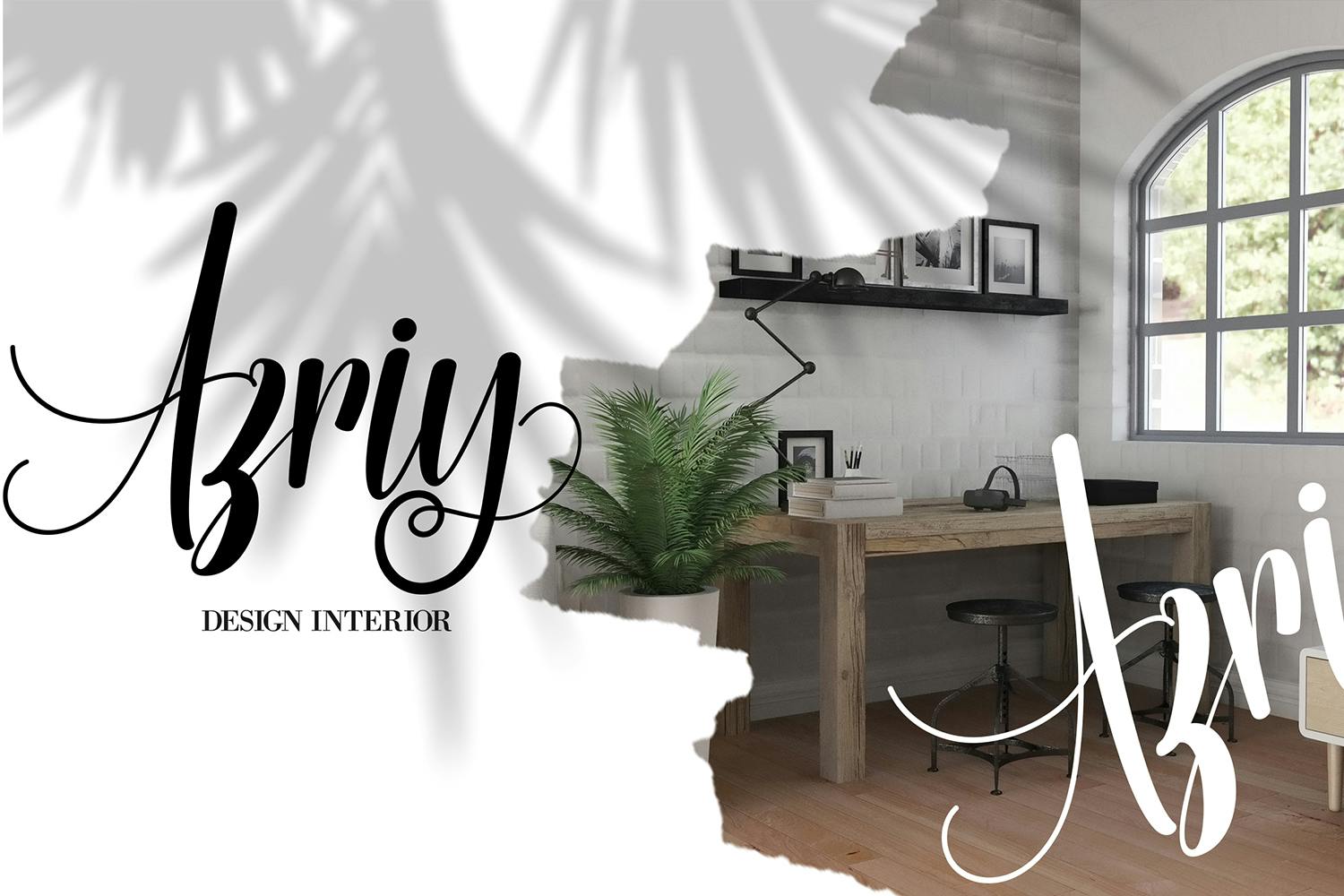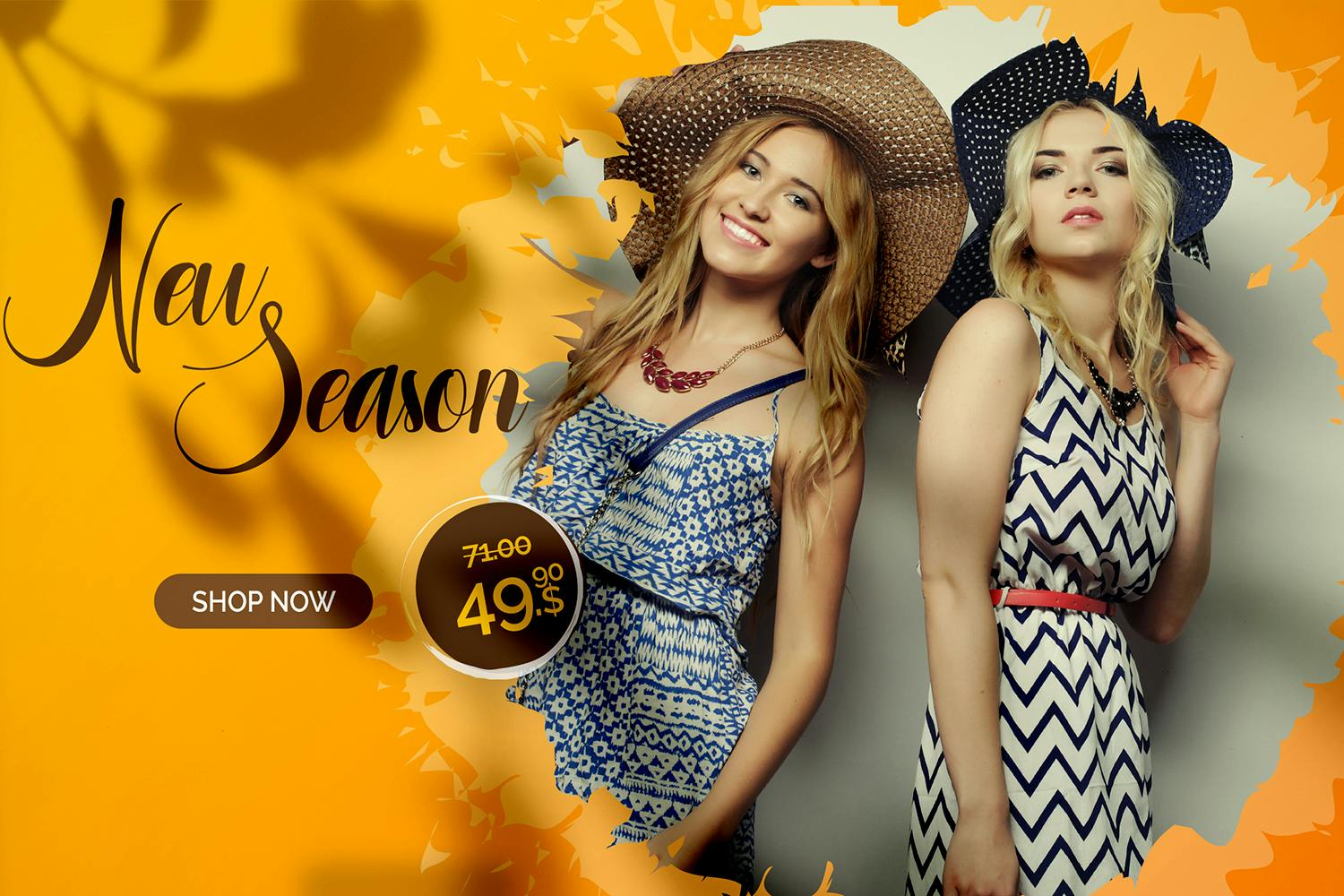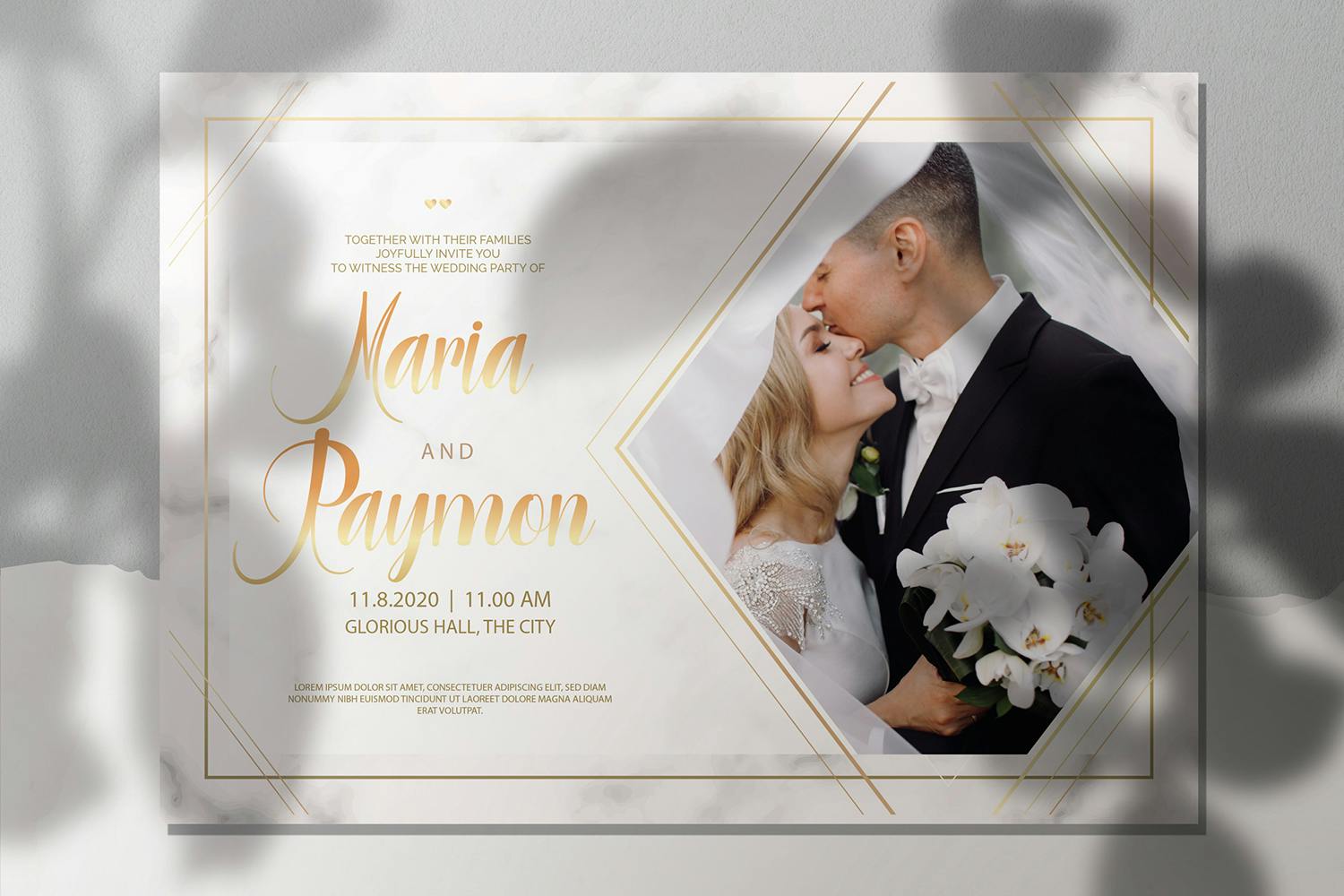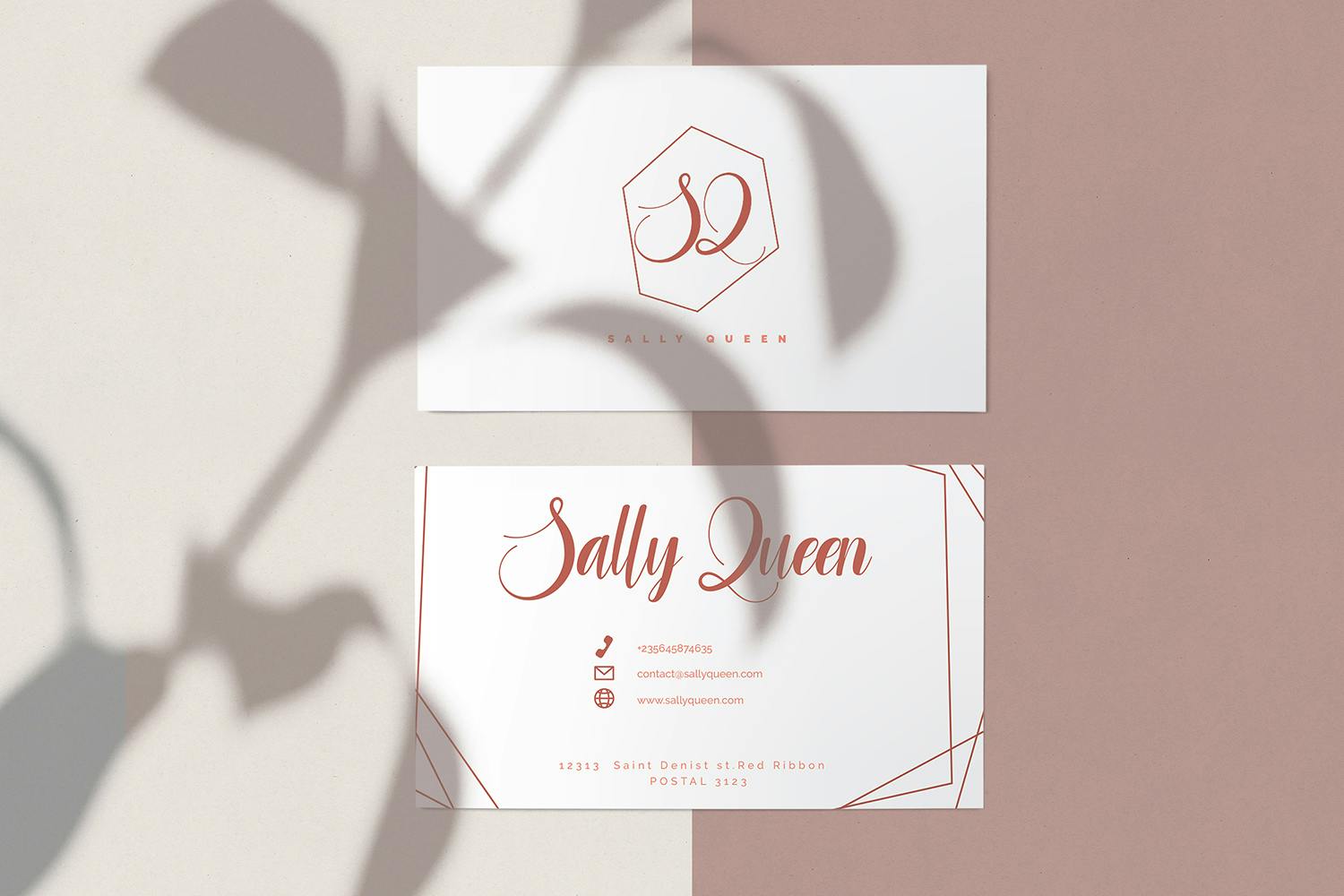
Hargery Molly | فونت خوشنویسی لوکس با سبک خوشنویسی، بسیار زیبا برای دعوتنامهها، کارتهای تبریک، مواد برندینگ، کارتهای ویزیت، نقلقولها، پوسترها و بیشتر!
حروف جایگزین به چندین ویژگی Open Type تقسیم شدهاند، مانند مجموعههای استایلیستی، جایگزینهای متنی، SWASH و Ligature. ویژگیهای Open Type را میتوان با استفاده از برنامههای Open Type مانند Adobe Illustrator، Adobe InDesign، Adobe Photoshop Corel Draw X و Microsoft Word دسترسی یافت. این فونت دارای کدگذاری PUA یونیکد (فونتهای بهخصوص کدگذاری شده) است، بنابراین تمام حروف جایگزین بهراحتی قابل دسترسی هستند.